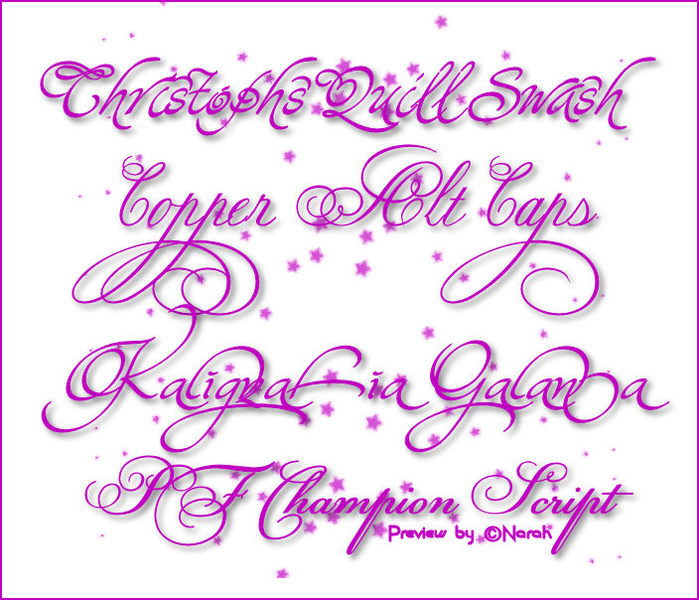
Бесплатно шрифты для фотошопа: Скачать бесплатные шрифты для Photoshop
Многие пользователи сталкиваются с такой ситуацией, когда нужен какой-то необычный и уникальный шрифт в фотошопе. К примеру, при создании поздравительной открытки, афиши и т.д. Стандартного набора шрифтов уже становится мало.
2. Установка шрифтов в Windows.
Здесь уже можно просмотреть все установленные в вашей операционной системе шрифты. Сама процедура установки происходит несколько иначе. Здесь нужно в меню «Файл» выбрать пункт «Установить шрифт».
Далее откроется окошко выбора шрифтов. Нужно открыть папку, в которой лежат файлы новых шрифтов, а затем выделить те из них, которые нужно установить. В конце жмем «Ок» и дожидаемся окончания процедуры.
Особенность данного способа – установленные шрифты будут доступны во многих программах, однако сам Photoshop может и не увидеть некоторые из этих шрифтов.
Поэтому, если новые шрифты нужны вам исключительно для фотошопа, то целесообразно пользоваться 1 методом установки.
10 лучших шрифтов Photoshop для использования в Creative Cloud
Типография – одна из самых красивых и разочаровывающих частей графического дизайна. Гарнитуры могут оказать огромное влияние при правильном использовании. И наоборот, к сожалению, тоже верно. Имея это в виду, вот лучшие шрифты Photoshop, доступные в качестве стандарта.
Выбор правильного семейства шрифтов
При поиске подходящего семейства шрифтов – и есть много доступных вариантов – как вы решаете, какой из них подходит именно вам? Photoshop CC поставляется с различными встроенными шрифтами, полезными для любого случая, и мы постарались найти лучшие для вас.
Прежде чем мы начнем, если вы новичок в типографии, мы рекомендуем вам проверить наше объяснение наиболее важных терминов типографии
5 самых важных типографских терминов
Прочитайте больше
, Это поможет вам понять, о чем мы говорим в оставшейся части статьи.
1.
Начнем с Times New Roman. Вы ищете шрифт, который легко читается или не слишком кричащий? Тогда Times New Roman – одна из ваших лучших ставок. Это один из самых широко доступных шрифтов, и Photoshop сделал все возможное, включив его в программу.
Первоначально созданный в 1920-х годах, Times New Roman обычно используется для основного текста в газетах, журналах и книгах. Это одобрено для его удобочитаемости и его универсального доступа через цифровые программы.
2. Баскервиль
Еще одним «классическим» шрифтом, который поставляется с Photoshop, является Baskerville: гладкая, немного «более легкая» альтернатива Times New Roman, с такими же легкими для чтения способностями и консервативным использованием пространства. Это не займет много места на странице, когда вы примените его.
Хотя Баскервиль не так популярен, как Times New Roman, он одинаково хорошо подходит для основного текста и может функционировать как текст для вашего заголовка.
3. Американская пишущая машинка
Вы ищете шрифт с засечками, который хорошо работает как основной текст в абзаце? Хотите что-то более современное и повседневное, чем Times New Roman? American Typewriter – хороший ответ на этот вопрос, и он может придать вашим документам «ретро» вид.
4. Edwardian Script ITC
Теперь, когда мы прошли основы, что если вам нужен шрифт, похожий на рукописный скрипт?
В Photoshop есть пара таких, но одним из лучших является ITC Edwardian Script: элегантный, хорошо сбалансированный шрифт, который отлично смотрится на свадебных приглашениях, поздравительных открытках и приглашениях на вечеринки.
Однако мы не рекомендуем использовать этот текст для основного текста, потому что он не такой разборчивый, как другие в этом списке.
5. Монтсеррат
Конечно, не все шрифты будут выглядеть «классически», как и вы.
Возможно, вы ищете удобный для Интернета шрифт, который хорошо выглядит на мобильных устройствах, или что-то, что ближе к современным тенденциям дизайна. Одним из наиболее полезных шрифтов, попадающих в эту категорию, является Монтсеррат с жирными, широкими буквами, что делает его идеальным для названий и заголовков. Я использовал это на своем собственном сайте в течение многих лет.
Слово предупреждения – этот шрифт не подходит для основного текста. Его большой размер означает, что это космический убийца.
6. В. Готика
Century Gothic – это шрифт без засечек с чистым, более легким на вид линейным весом по сравнению с чем-то вроде Montserrat. Вы можете использовать его для заголовков и заголовков, и если вы будете осторожны, это также хорошо для коротких абзацев. Но будьте осторожны, если эти абзацы слишком длинные, Century Gothic затруднит их чтение.
7. Helvetica
Трудно выбрать, какие шрифты являются лучшими, потому что их так много. Отчасти это зависит и от личного вкуса. Если вы ищете простую современную гарнитуру, которая работает практически со всеми дизайнами – от профессиональных отчетов до туристических брошюр – тогда лучше всего использовать Helvetica.
Helvetica – это широко используемый шрифт, который славится своей универсальностью и удобочитаемостью. Он хорошо работает для заголовка, заголовков и основного текста, а поскольку буквы расположены так красиво, что сложно испортить свой дизайн после их применения.
8. Фосфат
Лучше всего сохранить «Фан» на последний раз, верно? Мы знаем, ужасный каламбур, но иногда вы хотите веселый шрифт для рекламы. Одним из лучших вариантов, включенных в Photoshop, является Phosphate – смелый, широкий шрифт, идеально подходящий для привлекающих внимание заголовков на постерах. Из-за его размера мы не рекомендуем использовать его для основного текста, но он отлично подходит для заголовков.
9. Баухауз 93
Ищете декоративный шрифт, который немного более пышный, дружелюбный и причудливый, чем фосфат? Баухауз 93 сделает свое дело. Как и его более тяжелый сосед, этот шрифт большой и жирный, и его лучше всего использовать для заголовков на плакатах и брошюрах.
10. Браггадосио
Наконец, что не менее важно, одним из лучших дизайнов в Сан-Сериф в Photoshop является Braggadocio – смелый, гиперстиллизованный шрифт, который сразу же требует внимания. Это хорошо для названий с ретро-дизайном, но используйте его экономно. Слишком много, и это сделает ваш текст трудным для чтения.
Каков лучший шрифт Photoshop для вас?
Теперь, когда вы получили представление о шрифтах, которые поставляются с Photoshop, вы должны попробовать их, чтобы увидеть, какие из них соответствуют вашим личным вкусам.
Как упоминалось ранее, дизайн может быть субъективным, и могут быть некоторые шрифты, которые не попали в этот список, который, по вашему мнению, лучше подходит для ваших документов. Мы рекомендуем вам просмотреть их все и посмотреть, что работает лучше для вас.
Если вы изучаете полный типографский пакет Photoshop и все еще не удовлетворены имеющимся выбором, вы всегда можете использовать сайт с гарнитурой для поиска и загрузки бесплатных семейств шрифтов. У нас есть список сайтов, которые помогут вам найти бесплатные шрифты в зависимости от внешнего вида.
Как найти бесплатные шрифты, похожие на платные шрифты по внешнему виду
Поиск идеального шрифта может быть проблемой, особенно если вы не можете позволить себе заплатить за него. Но с помощью этих инструментов вы сможете найти бесплатные альтернативы в течение нескольких минут.
Прочитайте больше
,
Узнайте больше о: Adobe Photoshop, шрифты, типографии.
5 функций программного обеспечения Google Pixel Camera, которые вы должны использовать
Шрифты для Фотошопа русские
Начинаем серию записей, где будут представлены кириллические шрифты, которые можно использовать для написания русский букв в программе Adobe Photoshop. Скачать шрифты для Фотошопа можно бесплатно с ЯндексДиска по прямым ссылкам. Любой шрифт можно использовать в Фотошопе CS6, CS5, CS4, CS3, CS2 и любой другой версии.
Для установки шрифта для Adobe Photoshop, его следует скачать и переместить в папку со шрифтами на рабочем компьютере, где установлен сам Фотошоп. В Windows 7 это папка: C:\Windows\Fonts или Панель управления\Оформление и персонализация\Шрифты.
Русский шрифт Parnas Deco
Красивый русский шрифт для Фотошопа, который подойдёт для создания большинства печатных изданий и иллюстраций.
Скачать бесплатно русский шрифт для Фотошопа Parnas Deco: СКАЧАТЬ ШРИФТ (с ЯндексДиска)
Русский шрифт Pasadena Deco
Данный русский шрифт для Adobe Photoshop отличается начертанием и тем, что и прописные и заглавные буквы в шрифте преобразуются в один стиль с заглавными буквами.
Скачать бесплатно русский шрифт для Фотошопа Pasadena Deco: СКАЧАТЬ ШРИФТ (с ЯндексДиска)
Русский шрифт PosteRetro
Заглавные буквы в этом шрифте отличаются от прописных лишь добавлением теней. Размеры прописных и заглавных букв практически одинаковые.
Скачать бесплатно русский шрифт для Фотошопа PosteRetro: СКАЧАТЬ ШРИФТ (с ЯндексДиска)
Русский шрифт Proletariat
В этом шрифте и прописные и заглавные буквы одинаковые.
Скачать бесплатно русский шрифт для Фотошопа Proletariat: СКАЧАТЬ ШРИФТ (с ЯндексДиска)
Русский шрифт New Record
Красивый русский шрифт для Adobe Photoshop, имитирующей письмо ручкой.
Скачать бесплатно русский шрифт для Фотошопа New Record: СКАЧАТЬ ШРИФТ (с ЯндексДиска)
Русский шрифт Rondo Twin
Скачать бесплатно русский шрифт для Фотошопа Rondo Twin: СКАЧАТЬ ШРИФТ (с ЯндексДиска)
Русский шрифт SambaC
Необычный шрифт, который отличает особенное начертание отдельных букв, в основном — согласные буквы.
Скачать бесплатно русский шрифт для Фотошопа SambaC: СКАЧАТЬ ШРИФТ (с ЯндексДиска)
Русский шрифт Severina
Простой русский шрифт для Photoshop с одинаковым начертанием заглавных и прописных букв.
Скачать бесплатно русский шрифт для Фотошопа Severina: СКАЧАТЬ ШРИФТ (с ЯндексДиска)
Русский шрифт Stradivari script
Не шрифт, а музыка! Красивые буквы, особенно строчные.
Скачать бесплатно русский шрифт для Фотошопа Stradivari script: СКАЧАТЬ ШРИФТ (с ЯндексДиска)
Photoshop Text
Here, you will learn the process of creating bloody text effect in Photoshop by using layer styles. Step 2 > Add Some Text Write anything you want over the texture. If you want to modify an existing Photoshop shortcut or create custom Photoshop shortcuts for commands that have no default shortcut, follow the instructions below: In Photoshop, go to Edit > Keyboard Shortcuts, or hit Alt + Shift + Ctrl + K (a shortcut to access the shortcut!). Creating amazing 3D text effects is one of the many things that can be done with all the available 3D Tools and Settings in the (relatively) new Photoshop Cs6’s 3D environment. Our Picsart Photo editing platform giving all latest Text Png from here.
Скачать бесплатные шрифты Photoshop | 50 лучших бесплатных шрифтов Photoshop
Если вы столкнулись с задачей добавления текста к фотографии, эти бесплатные шрифты Photoshop, разработанные профессиональными ретушерами фотографий, будут вам очень полезны. Не кладите поверх изображения первый попавшийся шрифт, ищите замечательный шрифт, который гармонично впишется в ваш фотографический стиль. Для вашего удобства команда FixThePhoto выбрала лучшие бесплатные шрифты для Photoshop, подходящие для различных типов фотографии.
50 бесплатных шрифтов для Photoshop
№1 Акиметр. Шрифт с простыми, легко читаемыми буквами подойдет для любого изображения, передающего важное сообщение. Края букв дополнены засечками для изысканного вида.
# 2 Apogear. Это лучший шрифт Photoshop, который можно применить, если вы хотите, чтобы текст выделялся. Он сочетает в себе толстые и тонкие линии с круглыми завитками.
Лучшие шрифты для фотографии — Выбор CreativeMarket
Загрузите шрифты в рекламных целях или для публикации в социальных сетях.Вы можете легко нанести текст на свои фотографии или дизайн в Ps.
Выберите шрифт, который соответствует вашему стилю и ощущениям от вашего искусства.
# 3 Aquataken . Еще один чистый шрифт, с небольшими дополнительными засечками по краям букв. Это универсальный фотографический шрифт, который наверняка впишется в любое изображение.
# 4 Аркон. Это один из лучших профессиональных шрифтов, для которого характерны слегка вытянутые буквы. Благодаря своей простоте он широко используется в печатных СМИ.
№ 5 Артоника. Считается одним из лучших полностью читаемых бесплатных шрифтов Photoshop для фотографий логотипов. Сочетание тонких и толстых линий, острых и закругленных краев придает тексту изысканный вид.
# 6 Необычные шрифты. Это бесплатный генератор шрифтов, который позволяет преобразовать текст в стильный шрифт прямо в браузере. Вам просто нужно ввести текст, выбрать понравившийся шрифт и скопировать
№ 7 Бардане. Если применить этот шрифт к тексту, он обязательно бросится в глаза. Необычное сочетание тонких и толстых штрихов, изогнутых завитков и случайных линий, расположенных внутри, на или под буквами, гармонирует с любым творческим фото-фоном.
№8 Буке. Если вам нужно привлечь внимание к тексту или сделать его более заметным, этот шрифт подойдет идеально. Он имеет жирные и толстые буквы с изогнутыми штрихами, которые выглядят довольно привлекательно.
№ 9 Кардоне. Входит в список лучших шрифтов Photoshop. Этот шрифт часто используется для текста, который выражает всевозможную информацию из-за единообразной формы букв и аккуратного внешнего вида.
№ 10 Карридж. Это один из лучших рисованных бесплатных стилей шрифтов Photoshop. Его уникальные изгибы и штрихи определенно модернизируют любой текст или заголовок.
№11 Чалсын. Это отличный шрифт с засечками для тех, кто ищет шрифты для логотипов фотографий.Буквы характеризуются тонкими и простыми линиями, которые способствуют освежающему виду текста.
№ 12 Читоса. Это один из самых узнаваемых шрифтов Photoshop для кистей. Смесь замысловатых линий и завитков добавит вашему тексту изюминки.
# 13 Чусарский. Вы не ошибетесь с этим шрифтом с засечками, если вам нужно, чтобы текст выглядел достаточно просто и минималистично. Буквы средней толщины с четкими линиями впишутся в любой образ.
# 14 Констанца. Название этого шрифта говорит само за себя — буквы постоянной формы, которые выглядят слегка жирными. Этот шрифт с засечками рекомендуется использовать для заголовков, например, на веб-сайтах.
# 15 Contaria. Это один из наиболее подходящих бесплатных шрифтов для съемки природы и пейзажей. Его округлые края дарят ощущение умиротворения и умиротворения.
# 16 Даулинк. Геометрические протяженные буквы шрифта дополнены тонкими и неровными мазками.Применяйте его, если вам нужно добиться гранжевого эффекта текста.
# 17 Затмение. Если вы ищете бесплатные шрифты для дизайнеров, то это один из них. Нежные и слегка закругленные края, разнообразное вращение букв сразу привлечет внимание к картинке и тексту.
# 18 Enjoyinalos. Еще один необычный шрифт, который выглядит так, будто нарисован кистью. Из-за этого эффекта буквы содержат пробелы, но они не усложняют чтение слов.
# 19 Envatic. Это один из самых простых и разборчивых бесплатных шрифтов Photoshop. Аккуратные и точные буквы отлично будут смотреться на однотонных и монохромных изображениях.
№20 Эполос. Он считается одним из самых элегантных шрифтов для подписи Photoshop. Буквы с точками по краям, красиво изогнутые длинные линии выглядят как настоящий почерк прошлых веков.
№ 21 Фантартика. Этот шрифт может служить отличным шрифтом для подписи. Соединенные буквы с изысканными завитками украсят любую фотографию и текст на ней.
№ 22 Пожарные. Среди лучших шрифтов для логотипов этот привлекает больше всего внимания. Благодаря своим особенностям, таким как неровные и слегка вытянутые буквы, шрифт эффективно используется для брендинга или упаковки.
№ 23 Фонтанце. Если вы ищете шрифты водяных знаков для фотографий, обратите внимание на этот.Его характеристики включают в себя тонкие завитки и жирные буквы с отчетливыми пустыми линиями, пронизывающими шрифт.
№ 24 Фраголлини. Шрифт навеян надписью на классной доске. Внутренние части букв покрыты тонкими неровными линиями. Вы можете применить этот шрифт к своим логотипам или для того, чтобы подчеркнуть название бренда.
№ 25 Готемика. Шрифт — прекрасное дополнение к списку рукописных гарнитур.Изысканные буквы с дополнительными завитками идеально впишутся в любой вид фотографии.
# 26 Ханстер. Еще один отличный рисованный бесплатный шрифт для Photoshop. Буквы с тонкими штрихами и завитками подходят как для профессиональных, так и для повседневных целей.
# 27 Linteras. В шрифте сочетаются толстые и тонкие линии с плавными изгибами. Буквы соединены и идеально подходят для применения к цитатам.
# 28 Litecrossin. Это очень минималистичный и легкий для чтения шрифт с чистыми линиями. Вам может потребоваться обвести текст этим шрифтом, чтобы слова были более заметными.
# 29 Ломарин. Этот шрифт невероятно сочетает жирные буквы с слегка изогнутыми краями. Используйте его, когда вам нужно сделать сильное заявление и привлечь внимание к тексту.
# 30 Меланна . Его можно охарактеризовать как один из самых изысканных бесплатных шрифтов для фотографии.Можно нанести буквы средней толщины с небольшими изгибами, чтобы выделить заголовок или цитату.
# 31 Midvalence. Это отличный бесплатный шрифт для Adobe Photoshop, немного похожий на Linteras. Но в этом шрифте буквы не связаны друг с другом, что делает его идеальным вариантом для заголовков, длинных или коротких.
№ 32 Монпанс. Среди бесплатных шрифтов для дизайнеров этот, безусловно, самый необычный.Буквы выглядят как настоящий, слегка неразборчивый почерк. Хотя это может быть отличным шрифтом для подписи, не рекомендуется использовать его для передачи важной информации.
# 33 Монрета. Если вы ищете универсальный шрифт, вы можете попробовать этот. Это шрифт с засечками, характеризующийся простыми и четкими буквами.
№34 Наласкина. Считается одним из лучших шрифтов для фотографов.Тонкие изящные буквы красиво сочетаются с любым фоновым изображением.
# 35 Оракл Дарк. Название шрифта может указывать на то, что он предназначен для мрачных и драматических снимков. На самом деле он вполне приемлем для различных целей из-за средней толщины букв с тонкими изогнутыми линиями.
# 36 Паладин. Этот шрифт входит в список лучших бесплатных шрифтов для скачивания. Преимущество заключается в его универсальности, аккуратности и точности надписей, подходящих для названий или упаковки.
№ 37 Патаганиар. Это один из самых фантастических бесплатных шрифтов для логотипов Photoshop. Его особенностями являются тонкие и изогнутые двустрочные буквы, которые также дополнят подходящий фото-фон.
№38 Президиум. Этот шрифт увеличивает список превосходных рисованных бесплатных шрифтов Photoshop. Курсивные буквы детализированы дополнительными завитками.
№ 39 Пурбанк. Охарактеризован как один из самых изысканных шрифтов фотографии. Сплошные, рукописные и слегка изогнутые буквы могут улучшить внешний вид любого текста.
№40 Растан. Он считается одним из многих привлекательных шрифтов Adobe Photoshop, которые можно бесплатно загрузить. Шрифт имеет нарисованные от руки буквы с небольшими изгибами, которые улучшат, например, изображение с коротким заголовком или цитатой.
# 41 Скристофер. Как один из самых ярких бесплатных шрифтов для подписи, его характеристики включают тонкие линии букв и изогнутые штрихи.Благодаря узнаваемому стилю, его также можно использовать для логотипов или заголовков.
№ 42 Шрамель. Вам никогда не хватит минималистичных бесплатных шрифтов Photoshop с засечками. Простые и чистые буквы этого шрифта средней толщины подходят для текста на однотонном фоне.
# 43 Сонтара. Этот шрифт по праву занимает свое место среди лучших шрифтов для фотошопа. Слегка закругленные буквы с изогнутыми краями определенно модернизируют внешний вид текста.
# 44 SpiritCon. Считается одним из лучших бесплатных шрифтов для дизайнеров. Очень тонкие буквы с небольшими изящными завитками обязательно увеличат «дух» вашего текста и изображения в целом.
# 45 Sunnysan. Еще один отличный шрифт среди упрощенных шрифтов для загрузки в Photoshop. Он имеет слегка вытянутые буквы одинаковой формы для четкого вида текста.
# 46 Валенс. Этот шрифт дополняет список невероятных бесплатных шрифтов Photoshop. В глаза бросается смесь толстых и тонких мазков с закругленными краями.
# 47 Винбарри. Шрифт имеет схожие характеристики с Valense. Только буквы у этого не наклонены, и его можно использовать в более профессиональных целях, например, для обложки журнала или книги.
№ 48 Виолетта. Он считается одним из лучших бесплатных шрифтов для Photoshop.Его изящные изогнутые буквы напоминают ретро-почерк. Из-за его особенностей используйте этот шрифт, чтобы добиться драматического эффекта.
№ 49 Виртуозо. Судя по названию, это один из самых необычных шрифтов с водяными знаками для фотографии. Вытянутые тонкие линии, большая разница между заглавными и строчными буквами оставят неизгладимое впечатление.
№ 50 Юнграндер. Это один из тех бесплатных шрифтов для Adobe Photoshop, которые на первый взгляд могут показаться обычными. Но на самом деле в его простоте и небольших завитках есть определенное очарование, которое может броситься в глаза при правильном применении шрифта.
Попробуйте и загрузите шрифты для Photoshop, разработанные FixThePhoto. Возможно, вам придется пройти через приличное количество из них, чтобы найти самые замечательные и вдохновляющие шрифты, но не бойтесь экспериментировать.
33 лучших бесплатных шрифта, которые следует загрузить дизайнерам
Поиск стильных шрифтов для ваших дизайнерских проектов может отнять у вас много времени, особенно когда вам приходится пробираться через кажущиеся бесконечными страницы шрифтов, которые не подходят для вашего видения. .
Найти бесплатный шрифт может быть еще сложнее.
Так что же делать дизайнеру с ограниченным бюджетом?
Мы исследовали все глубины Интернета, чтобы вам не приходилось делать это, придумав 33 лучших бесплатных шрифта, которые вы заслуживаете иметь на своем компьютере. Вот как мы их отсортировали:
Многие из представленных здесь бесплатных шрифтов были разработаны дизайнерами для дизайнеров, поэтому они не понаслышке понимают необходимость универсальных, отполированных и бесплатных шрифтов. Ознакомьтесь со шрифтами ниже и помните о них в своем следующем дизайнерском проекте.
Лучшие бесплатные шрифты для дизайнеров
- Hello Stockholm — шрифт скрипта
- Wildera Regular — шрифт шрифта
- Mightype — шрифт скрипта
- Selima — шрифт скрипт
- Oranienbaum Regular — шрифт с засечками
- Butler — шрифт с засечками
- Arctic — шрифт с засечками
- Canvas — шрифт с засечками
- Bitter ht — шрифт с засечками
- Agne Regular — шрифт с засечками
- Yeseva One Regular — шрифт с засечками
- Moon — современный шрифт
- Kolikö — современный шрифт
- Mohave — современный шрифт
- 20 дБ
- Alcubierre Regular — современный шрифт
- Bourbon Grotesque — современный шрифт
- Frontage Outline — современный шрифт
- Arciform Sans Regular — современный шрифт
- De La Fuente — современный шрифт
- Westfalia — шрифт для логотипов
- Atami — шрифт для логотипов
- Anders — шрифт для логотипов
- Westmeath — шрифт для логотипов
- Modeno — шрифт для логотипов
- Rezland — шрифт для логотипов
- Polya — шрифт для логотипов
- Horizon — ретро шрифт
- Sweet Sensations — ретро шрифт
- ITC Bauhaus — ретро шрифт
- Bobbers — ретро шрифт
- FF Blur — ретро шрифт
- Canterbury — ретро шрифт
Бесплатные скриптовые шрифты
1.
Что произойдет, если совместить скандинавский минимализм с классическими мазками? Вы получаете Hello Stockholm , случайный сценарий, который хорошо сочетается со шрифтами без засечек.
2. Wildera Regular
Мы думаем, что этот причудливый, легкий сценарий будет хорошо смотреться в сказке (или в вашем следующем проекте).
3. Mightype
Тонкие детали, нарисованные от руки, отличают этот сценарий от набора. Mightype изысканный, но не душный.
4. Селима
свежих мазков Селимы — прекрасное доказательство того, что шрифтовые шрифты не обязательно должны выглядеть старомодно или напряженно — они могут быть повседневными и современными.
Бесплатные шрифты с засечками
5. Ораниенбаум Обычный
Многозадачность — от мелкого шрифта до жирных заголовков — Oranienbaum справится с задачей.
6. Дворецкий
Совершенно современный шрифт с засечками, Butler , выпускается в 14 вариантах начертания, чтобы удовлетворить самые разные задачи.
7. Арктика
Если вы ищете шрифт с плоскими засечками с современными краями, попробуйте Arctic . Это отличный способ придать заголовкам особый характер.
8. Холст
Canvas предлагает скромный, но профессиональный шрифт, который изменяет толщину деталей каждой буквы. Если вы ищете формальности и креативности в одном и том же шрифте, этот вариант лучше всего.
9. Горький ht
Нам нравится универсальность Bitter ht, — современного шрифта с засечками, который выглядит стильно при любом размере и весе.
10. Agne Regular
Этот элегантный шрифт с жирными линиями и контрастными основами представляет собой свежий взгляд на старомодные гарнитуры с засечками.
11. Есева Один Обычный
Если вас беспокоит, что шрифты с засечками кажутся слишком строгими или формальными, рассмотрите вариант Yeseva , непринужденный вариант для заголовков и субтитров.
Бесплатные современные шрифты
12. Луна
Вы исчерпали свою библиотеку простых и бесплатных шрифтов без засечек? Добавьте к смеси Moon .Нам нравится чистая простота и округлые края этого шрифта.
13. Kolikö
Этот жирный шрифт придает загадочность любой творческой работе. Или, если вы просто хотите узнать о чем-то в своем новом техническом блоге, мы можем полностью увидеть, что этот шрифт играет определенную роль.
14. Мохаве
Этот шрифт, состоящий только из заглавных букв, был разработан с учетом жирных заголовков и больших настроек шрифта.
15. 20 дБ
Шрифт ниже просто неподвластен времени. Независимо от того, разрабатываете ли вы рекламу мероприятия или заголовки своего блога, 20 дБ — это уверенность в письменной форме.
16. Alcubierre Regular
Чистый, минималистичный и геометрический, Alcubierre хорошо подходит для проектов, требующих тонких заголовков и четкого акцента на содержании.
17. Бурбонский гротеск
Вдохновленный, как вы уже догадались, классическими этикетками из бурбона, этот без засечек обладает яркой индивидуальностью, требующей внимания.
18. Внешний вид
Frontage Outline напоминает фасадные вывески ручной работы, что делает его подходящим выбором для логотипов.
19. Arciform Sans Regular
Arciform может быть простым, но этот гладкий шрифт без засечек далеко не скучный. Подумайте о том, чтобы включить этот легкий для чтения шрифт в свой следующий проект веб-дизайна.
20. Де Ла Фуэнте
Этот классный шрифт является декоративным, но не чрезмерным, что делает его идеальным для заголовков, логотипов и других дизайнерских проектов, в которых основное внимание уделяется тексту.
Хорошие шрифты для логотипов
21. Вестфалия
Придайте своему следующему проекту атмосферу естественности и аутентичности с помощью этой расписанной вручную кисти без рисунка, которая также создает игривый логотип.
22. Атами
Многочисленные веса и варианты отображения Atami делают его швейцарским армейским ножом среди современных шрифтов без засечек — он действительно может сделать все это для растущего бренда.
23. Андерс
Anders может стать авангардным шрифтом вашей мечты. Уникальные геометрические линии делают его отличным выбором для логотипов.
24. ВестмитWestmeath добавляет немного чванства к основному шрифту, делая логотип, использующий этот шрифт, разборчивым и стильным.
25. Модено
Шрифт Modeno соответствует тонкому дизайну, к которому в последние несколько лет тяготели многие современные художники. Но не путайте этот шрифт с любым шрифтом новой волны — его долговечные качества трудно найти в сегодняшних вариантах без засечек.
26. Резланд
Резланд просто крут. У него почти нет времени для вас … вот насколько круто этот выбор шрифта.
27.Поля
Polya , пожалуй, самый интересный шрифт, который мы могли найти. Тесьма каждой буквы создает поистине завораживающий логотип.
Бесплатные ретро шрифты
28. Горизонт
Horizon — простой, но ретро-шрифт, воспроизводящий изображения старого космического фильма. И тем не менее, он все еще остается в силе.
29. Сладкие ощущения
30. ITC Bauhaus
Подобно Horizon, ITC Bauhaus имеет округлый ретро-вид, который бывает разной толщины.Более толстые версии выглядят как заголовок старой афиши, а более тонкие стили создают джазовую атмосферу.
31. Бобберы
Bobbers — это скриптовый шрифт, обладающий бестолковыми и чрезмерными качествами старого комедийного сериала. Верните его из 1970-х в свой следующий дизайн-проект для действительно уверенного заголовка.
32. Размытие FF
Призрачное сияние FF Blur напоминает нам старый фильм ужасов. Но он может быть достаточно мягким, чтобы заинтриговать аудиторию вашего следующего проекта.
33. Кентербери
Ни один список старомодных шрифтов не будет полным без староанглийского стиля Кентербери. Подражайте многим из самых известных сегодня газетных логотипов с помощью этого традиционного шрифта.
Мы надеемся, что вы найдете эти шрифты полезными, но поскольку они предлагаются другими сторонами на их сайтах, мы не можем давать никаких гарантий или обещаний в отношении них (например, что они будут доступны или бесплатны для использования).
Также мы хотим упомянуть, что дизайнеры, предлагающие эти шрифты, могут иметь правила о том, как вы можете или не можете их использовать, поэтому могут быть ограничения, применимые к использованию шрифта.
Хотите больше советов по шрифтам? Ознакомьтесь с этим советом по определению названия шрифта.
25 великолепных бесплатных шрифтов для вашего следующего дизайн-проекта
Шрифты для дизайнеров — то же самое, что обувь для женщин. Их никогда не может быть достаточно. А что лучше красивого шрифта? Красивый шрифт, доступный БЕСПЛАТНО. Мы составили список из 25 стильных и современных шрифтов, которые понравятся дизайнерам.Ознакомьтесь с ними ниже.
1. Луна
Скачать шрифт2. Бухты
Скачать шрифт3. Большой Джон / Тонкий Джо
Скачать шрифт4. Барон
Скачать шрифт5. Порту
Скачать шрифт6. Элероны
Скачать шрифт7. Винтаж и эрозия
Скачать шрифт8. Акцентный дисплей
Скачать шрифт9. Simplifica
Скачать шрифт10.Андерс
Скачать шрифт11. Бесконечность
Скачать шрифт12. Мохаве
Скачать шрифт13. Adam.CG Pro
Скачать шрифт14. Aqua Grotesque
Скачать шрифт15. Байдарка Sans
Скачать шрифт16. Причал
Скачать шрифт17. Котенок
Скачать шрифт18. Бесом
Скачать шрифт19.Moderne Sans
Скачать шрифт20. Мантека
Скачать шрифт21. Фасад
Скачать шрифт22. Ось
Скачать шрифт23. Коко
Скачать шрифт24. Плотный
Скачать шрифт25. Код
Скачать шрифтПОДРОБНЕЕ…
Какой ваш любимый? Надеюсь, этот пост пригодился. Поделитесь этим постом с другом-дизайнером и выскажите свое мнение в комментариях ниже.
Не пропустите:
- 32 блестящих логотипа со скрытым смыслом
- Графический дизайнер исправил 9 худших логотипов в истории
- 10 лучших документальных фильмов Netflix для графических дизайнеров
- Google AutoDraw бесплатно превращает ваши грубые каракули в красивые значки
- 30 Отличные сочетания шрифтов для вашего следующего дизайн-проекта
- 15 отличных сочетаний шрифтов Google для вашего следующего дизайн-проекта
профессиональных шрифтов | FontSpace
Загрузить- Темный режим
- Помощь Войти
- Шрифты
- Стили
- Коллекции
- Генератор шрифтов
- (͡ ° ͜ʖ ͡ °)
- Дизайнеры бесплатно
Cool
Cursive
Script
Симпатичный
Рукописный ввод
9035 903 903 903
9035 Serial
Современный
Логотип
Декоративный
Элегантный
Закругленный
Красивый
9028
- 9035 9035 Чистый
- 9035
Ссылка
Unicode
Название
Заголовок
Футуристический
Capital
Классический
SpaceДисплей
Заголовок
Брендинг
Женский
Журнал
Техно
28 Корпоративный- используйте
Сортировать по
- Популярные
- В тренде
- Новейший
- Имя
Личное использование Бесплатно
856k загрузок
Персональное использование Бесплатно
Обычный8420 загрузок
Для личного пользования Бесплатно
9993 загрузки
Личное использование Бесплатно
160.7k загрузок
Personal Use Free
26476 загрузок
Личное использование Бесплатно
152.9k загрузок
100% бесплатно
Обычные21694 загрузки
Для личного пользования Бесплатно
6588 загрузок
Личное использование Бесплатно
Straight Regular8286 загрузок
Personal Use Free
89665 загрузок
Личное использование Бесплатно
323 загрузки
100% бесплатно
Обычный9571 загрузок
Для личного пользования Бесплатно
287.1k загрузок
Personal Use Free
54116 загрузок
Личное использование Бесплатно
51627 загрузок
От 1 до 15 из 306 Результаты
- 1
- 2
- 3
- 4
- Next
Еще больше стилей
0
- Популярные шрифты
- Коммерческие шрифты
- Классные шрифты
- Курсивные шрифты
- Блог
- Справка
- Связаться с
- Бренд
- Конфиденциальность
- Условия
- DMCA 921-2010
60 великолепных и креативных бесплатных шрифтов для дизайнеров
2Добро пожаловать на третий день недели бесплатного пользования на Designrfix.Сегодня мы собрали потрясающую коллекцию самых красивых и креативных бесплатных шрифтов для дизайнеров. Так что, если вы ищете действительно классные бесплатные шрифты для своего последнего проекта, этот пост нельзя пропустить. Не стесняйтесь загружать и использовать их в своем следующем дизайне. Надеюсь, они вам понравятся, и завтра смотрите следующую бесплатную партию!
Хотите больше статей из Freebie Week ? Ознакомьтесь с некоторыми из наших предыдущих сообщений:
Бесплатные файлы PSD: более 50 файлов Photoshop, которые необходимо иметь для дизайнеров
40 бесплатных иконок социальных сетей с хорошим дизайном
Связано: Получите логотип за считанные минуты с помощью бесплатного конструктора логотипов от designhill.com
[m2leep]Лента
[AdSense]Intro бесплатный шрифт
Шрифт Stiff Staff
Архив
ГУБЕРНАТОР АЛФАВИТА АРТ ДЕКО
РБNo2
килограмм
бесконечность
Шрифт Hagin
Prime Шрифт
FV Алмело
[AdSense]Rex Бесплатный шрифт
Forum Шрифт
КОД Pro
Color Lines Бесплатный шрифт
Шрифт KanKin
Habana Шрифт
Cube 02 шрифт
Cube шрифт
Бендер Шрифт
Muncie Шрифт
CROISSANT — Бесплатный веб-шрифт Google
NULL Бесплатный шрифт
Cassannet Шрифт
[AdSense]Facunda Шрифт
Разноцветные шрифты
PLSTK Шрифт
Шрифт Chrome Light
Myra шрифт
Metropolis бесплатный шрифт
Баркентина Гарнитура
Шрифт Авраама Линкольна
Signika шрифт
Сценарий мудрости
Шрифт Ranger
Шрифт Blanch
Manteka Шрифт
RIDGE Гарнитура
Nelma Шрифт
Maven Pro
Шрифт Musket
Гарнитура Magna
Шрифт Origram
Code Free Шрифт
Шрифт Tetra
Шрифт Razor
Franchise Шрифт
Mensch шрифт
Валенсия Шрифт
Deming Шрифт
Duke Шрифт
Сценарий миссии
Лавандерия
Johanna Font
Цифры Pompadour
Sreda бесплатный шрифт
Atreyu Шрифт
Arvil Шрифт
Шрифт сбоя
Тип настроения
27 Красивые высококачественные бесплатные шрифты — Smashing Magazine
Время от времени мы смотрим вокруг, выбираем свежих бесплатных высококачественных шрифтов и представляем их вам в кратком обзоре.Выбор огромен, поэтому время, которое вам нужно найти, обычно — это время, когда вы должны инвестировать в свои проекты. Мы ищем их и находим, чтобы вам не пришлось. В этой подборке мы рады представить шрифты Tondu, Banda, Morning Glory, Matilde, Bohema, Weston Round Slab, Highlands, Cabin, Linden Hill и другие. Обратите внимание, что хотя большинство шрифтов доступны для коммерческих проектов, некоторые предназначены только для личного использования и четко обозначены как таковые в их описаниях. Также внимательно прочтите лицензионные соглашения перед использованием шрифтов; они могут время от времени меняться.Время от времени мы смотрим вокруг, выбираем свежих бесплатных высококачественных шрифтов и представляем их вам в кратком обзоре. Выбор огромен, поэтому время, которое вам нужно найти, обычно — это время, когда вы должны инвестировать в свои проекты. Мы ищем их и находим, чтобы вам не пришлось.
В этой подборке мы рады представить шрифты Tondu, Banda, Morning Glory, Matilde, Bohema, Weston Round Slab, Highlands, Cabin, Linden Hill и другие шрифты. Обратите внимание, что хотя большинство шрифтов доступны для коммерческих проектов, некоторые предназначены только для личного использования и четко обозначены как таковые в их описаниях.Также внимательно прочтите лицензионные соглашения перед использованием шрифтов; они могут время от времени меняться.
Дополнительная литература по SmashingMag:
Новые высококачественные бесплатные шрифты
Bohema Bohema — уникальный шрифт в стиле ар-деко в современной интерпретации. Непредсказуемость некоторых глифов делает его оригинальным и интересным, хотя иногда и немного хлопотным. Bohema доступна в восьми различных стилях и может отлично подходить для заголовков, редакционных надписей, брендинга, мерчендайзинга и особых случаев.Вы можете бесплатно загрузить один вес, Bohema Regular Alternative, хотя он не так полезен, как остальные шрифты из семейства шрифтов.
Highlands — это очаровательный шрифт с плоскими засечками, вдохновленный плакатами старых добрых национальных парков США. Шрифты, разработанные Тайлером Галпином, отлично подходят для заголовков и плакатов. В настоящее время доступен только набор заглавных букв. Выпущено по лицензии «плати сколько хочешь».
Бендер Семейство шрифтов Bender — это экстравагантный русский шрифт для особых случаев.Используйте его для графического дизайна, портфолио или полиграфической продукции. Доступны восемь размеров шрифтов, все они доступны для бесплатной загрузки. Но регистрация на MySpace обязательна.
Овальный тип Экспериментальный игривый шрифт, основанный на формах овала и круга. Очевидно, что он не подходит для корпоративных или элегантных проектов, но Ovalian Type может быть весьма полезен в проектах, которые требуют экспериментов, взаимодействия и творчества. Доступен в формате TrueType.
Linden Hill — это цифровая версия Deepdene Фредерика Гуди.Это небольшое семейство с засечками, разработанное Барри Шварцем, включает в себя римский шрифт и курсив. Linden Hill доступен в формате OpenType по лицензии SIL Open Font License.
Fanwood — это тщательно продуманный шрифт с засечками, напоминающий классический римский шрифт. Пакет шрифтов включает в себя римский и курсивный стили, оптимизированные для экрана. Это отличный шрифт, приятный при чтении, в том числе в заголовках и основном тексте. Выпущено под лицензией SIL Open Font License).
Матильда Приятный тонкий шрифт с очень высокими заглавными буквами и тонкими декоративными элементами. Матильда отлично подойдет для заголовков, коротких абзацев, детских книг, плакатов и брошюр. Семейство содержит 212 символов и глифов. Доступны два стиля: Обычный и Эскиз. Шрифт также содержит декоративные рамки и узоры.
Weston Round Slab Этот шрифт содержит закругленные плоские шрифты с засечками, разработанные Павловым специально для использования в логотипах и заголовках.Обычные и облегченные версии с заглавными буквами доступны в форматах OpenType для бесплатного скачивания.
Шрифт Banda Banda — это шрифт с полутонами с засечками, характеризующийся высокой высотой x и закругленными полутонами. Хотя изначально Banda был разработан как дисплейный шрифт, он быстро превратился в более сложный набор, состоящий из семи начертаний плюс их уважительный курсив. Банда может использоваться как для коротких отрывков текста, так и для модных демонстраций. Объединяя элегантную утонченность более тонких гирь с почти детской игристостью более тяжелых гирь, Banda — отличный универсальный исполнитель, подходящий для логотипов, заголовков, упаковки, пищевых продуктов и многого другого.
Black & White(Ссылка была удалена из-за нарушения авторских прав. Оригинальный дизайн — Calypso, разработанный литейным заводом Typolar.) Экспериментальный шрифт с двумя начертаниями шрифта (обычным и курсивом). Шрифт имеет множество отличительных игривых элементов, которые придают заголовкам неповторимый стиль ретро. Шрифт содержит английские и кириллические буквы и доступен в форматах OpenType и True Type.Обратите внимание, что в обоих форматах маленькая буква «j» не работает должным образом.Мы связались с дизайнером по поводу проблемы и надеемся, что шрифт скоро будет обновлен.(Проблема устранена.)Fabrica Practice Foundry — это независимый производитель шрифтов, выпускающий шрифты по лицензии «плати сколько хочешь». Шрифт без засечек был задуман как самый разборчивый шрифт для мобильных экранов. Его детали взяты из более систематически построенных нео-гротесков, что придает ему нейтральный тон голоса. Хотя Fabrica была разработана в первую очередь для мобильных экранов, шрифт подходит для любого приложения, большого или маленького.Шрифт доступен в формате OpenType для Mac и ПК.
ARS Новинка Этот шрифт — результат нестандартного подхода Ангуса Р. Шамала. Дизайнер придумал забавный и ни в коем случае не менее функциональный эксперимент с гибридными стилями и историческими влияниями, соединив барокко с засечками с геометрическим шрифтом без шрифта, формальный с декоративным штрихом. ARS Novelty — это, по-видимому, шрифт, который пытается все понять. Доступен единый вес со стилистическими альтернативами, цифрами, стандартными лигатурами и произвольными лигатурами, формами с учетом регистра, порядковыми и локализованными формами.В формате OpenType.
Беван Bevan — это переработка традиционного шрифта с засечками, созданного Генрихом Йостом в 1930-х годах. В Беване ранние формы букв Йоста были оцифрованы, а затем переделаны для использования в качестве веб-шрифта. Счетчики были немного приоткрыты, а штрихи оптимизированы для использования в качестве жирного шрифта в современных веб-браузерах. Это хороший выбор для жирных заголовков и рекламных брошюр. Выпущено по лицензии SIL Open Font License и доступно в репозитории Google Web Fonts.Дизайн Вернон Адамс. Возможно, вы захотите взглянуть на другие бесплатные шрифты Вернона Адамса: Rokkitt, Shanti, Muli.
Sansus Webissimo Этот шрифт представляет собой современный открытый гротескный шрифт, доступный в форматах OpenType и TrueType. Sansus потенциально отлично подходит как для заголовков, так и для основного текста, как в Интернете, так и в печати. Доступны две толщины шрифта: обычный и курсив. Семейство выпущено под лицензией Creative Commons Attribution 3.0 License.
Quattrocento Roman — классический, элегантный и сильный шрифт, которому, возможно, не хватает зрелости в некоторых деталях (например, «g» и «e» не совсем подходят друг другу).Шрифт имеет широкие и открытые буквы, а хорошая высота по оси x делает основной текст разборчивым даже при небольших размерах. Как классический римский шрифт Quattrocento — хороший выбор для крупных жирных заголовков. Исходные файлы Fontlab включены в пакет загрузки. Quattrocento Sans, доступный в виде веб-шрифта, также можно загрузить бесплатно.
Танцевальный сценарий Dancing Script — это живой и непринужденный сценарий, в котором буквы подпрыгивают и слегка изменяются в размере. Шрифт отсылает к популярным гарнитурам 50-х годов.Он напоминает Мюррея Хилла (Эмиля Клумппа, 1956) по распределению веса и Мистраля (Роджера Экскоффона, 1953) по его эффекту подпрыгивания. Dancing Script может быть полезен, если вы ищете непринужденный, дружелюбный, неформальный и спонтанный шрифт, а также неплохую замену Comic Sans! Также доступен в виде веб-шрифта.
Кабина Cabin — это гуманистический шрифт без засечек, вдохновленный шрифтами Эдварда Джонстона и Эрика Гилла с элементами модернизма. Кабина вобрала в себя современные пропорции, оптические корректировки и некоторые элементы геометрической формы.По словам дизайнера, «он остается верным своим корням, но имеет свою индивидуальность». Отличный шрифт для основного текста и заголовков на маленьких и больших экранах. Доступны четыре толщины шрифта с соответствующими стилями курсива.
Logisoso — это постоянный проект шрифтового дизайна. Шрифт, созданный во время проекта вывески для логистического центра, где он использовался для обозначения различных зданий, был позже дополнен с помощью Inkscape и сгенерирован с помощью FontForge. Пакет загрузки содержит исходные файлы для улучшения и оптимизации шрифта.
Novecento — это семейство шрифтов только с прописными буквами, вдохновленное европейскими типографскими тенденциями первой половины 20 века. Гарнитура выглядит рациональной, геометрической и блочной. Но он основан на оптических, а не геометрических пропорциях. Novecento можно использовать для заголовков, визуальных обозначений и коротких предложений. Более легкие веса придают более современный вид, а более смелые — в стиле ретро.
Ubuntu Семейство шрифтов Ubuntu — это набор новых открытых шрифтов без засечек.Семейство включает в себя все языки, используемые пользователями Ubuntu по всему миру. Разработан Далтоном Маагом для операционной системы Ubuntu и с открытым исходным кодом.
Ультра Красота Ultra заключается в ее смелости. Этот декоративный западный шрифт с элегантными засечками имеет резкое и привлекательное присутствие, особенно в тонких тонах «J», «7» и «f». Шрифт имеет расширенный европейский набор символов и доступен для бесплатной загрузки в формате TrueType. Под лицензией Apache License версии 2.
CS Бенвуд Этот шрифт уникален и подходит для самых разных работ по полиграфическому дизайну, будь то плакаты, обложки компакт-дисков или любой другой проект, требующий нетрадиционного типографского оформления. Каждый глиф имеет свой уникальный «древесный» вид. Разработано BenChalit Sagiamsak и доступно в формате OpenType.
Пять минут Этот шрифт был создан Олегом Журавлевым и предназначен для иллюстраций, отображающих ваш мозговой штурм и другие творческие идеи. Буквы не совсем оптимизированы и кажутся немного рыхлыми, но и от своих набросков большего вы не ожидаете.Шрифт содержит 151 глиф, включая латинский и кириллический алфавиты, цифры и некоторые специальные символы.
Maven Pro — это бесплатный шрифт без засечек с уникальной кривизной и плавным ритмом. Обширная коллекция символов насчитывает более 530 символов! Поддерживаются многие языки (их слишком много, чтобы перечислить), включая базовую латиницу и западноевропейские диакритические знаки. Огромное количество глифов позволяет использовать его практически для любого текстового контента: электронных таблиц, документов и особенно веб-сайтов.Шрифт также отлично подходит для печатных материалов и может очень сильно уменьшаться, сохраняя при этом разборчивость. Доступен в четырех стилях: черный, жирный, обычный и средний.
TypoFlat Основатель Typoflat Бранислав С. Циркович любит экспериментировать с шрифтом. На веб-сайте компании есть ряд экспериментальных векторных шрифтов (доступен только формат EPS), все они доступны для бесплатного скачивания и использования.
Никайя Компания Miller Type Foundry выпустила для бесплатного скачивания три толщины шрифта из своего семейства шрифтов Nikaia.Nikaia — футуристический геометрический шрифт для заголовков и основного текста. Nikaia, Nikaia Regular Italic и Nikaia Script выпущены бесплатно. Чтобы скачать файлы, вам необходимо зарегистрироваться на MyFonts.
Eau Sans Этот шрифт без засечек был первоначально разработан Ямаока Ясухиро в 1992 году, но глифы красивой формы делают его вневременным и надежным инструментом для любой типографской работы. Семейство состоит из шести начертаний шрифта с числовыми символами в трех вариантах: пропорциональный, в старом стиле и цифры с выравниванием.
Подкова представляет собой монолинейную плитку с засечками с диагональными окончаниями. Широкие пропорции и чистые элементы помогают разборчивости на небольших размерах. Необычные формы букв обеспечивают достаточно символов, чтобы их можно было использовать на дисплеях любого размера. Создан Ильей Юдиным в 2010 году.
Last Click
Сила типографики Да пребудет с вами сила типографики! Маттео Чиваски и Джанмарко Милези доказали, что сила типографики может выходить далеко за рамки традиционного текста и заголовков. Вы когда-нибудь пробовали создать шрифтом Йоду, штурмовиков или Дарта Вейдера? Что ж, у них есть.И результат не менее впечатляющий!
Связанные сообщения
Вам могут быть интересны следующие связанные сообщения:
(al)Free For All: 103 Free Fonts!
В этом выпуске «Бесплатно для всех» я расскажу только об одном типе халявы: всеобщие любимые бесплатные шрифты! Вы найдете скриптовые шрифты, современные шрифты, забавные шрифты и многое другое. В общем, в этой статье более 100 бесплатных шрифтов — этого достаточно, чтобы даже самый крупный компьютерный фанат головокружительно строил спецификации шрифтов в течение нескольких недель!
Обратите внимание, что лицензии на шрифты ниже варьируются от личного использования до бесплатных для коммерческого использования.Некоторые из обоих типов требуют указания автора. Пожалуйста, проверьте лицензию на любой шрифт, который вы загружаете, прежде чем использовать его в проекте. И еще одно предостережение относительно бесплатных шрифтов: www.creativepro.com/blog/typetalk-are-free-fonts-worth-price.
Просто щелкните изображение, чтобы загрузить шрифт или перейти на страницу со ссылкой для загрузки. Но прежде чем вы начнете играть со своим новым типом, пожалуйста, нажмите кнопку «Комментарии» и расскажите мне, что вы хотели бы видеть в будущих выпусках «Бесплатно для всех.«Я вернусь к обычному формату пяти различных типов бесплатных ресурсов и инструментов в моей следующей статье.
Гранж шрифтыВ народе называемые «гранжевыми шрифтами», группа шрифтов, официально классифицируемых как «проблемные», впервые стала популярной в результате обращения с заголовком в телешоу 1990-х годов «Секретные материалы» (загрузите его ниже!) И тяги к их только увеличилось с тех пор. Следующие бесплатные шрифты в стиле гранж должны утолить вашу жажду — по крайней мере, на время.
Рукописные и рисованные шрифты
Подберитесь ближе и лично со шрифтами, основанными на реальном почерке других людей и на нарисованных от руки формах букв.
Больше после прыжка! Продолжайте читать ниже ↓
Пользователи Free и Premium видят меньше рекламы! Зарегистрируйтесь и войдите в систему сегодня.
Хотя «фанковые шрифты» не являются традиционной классификацией шрифтов, это лучшее описание для следующего разнообразного ассортимента шрифтов.
Эта категория зарезервирована для шрифтов, которые извлекают выгоду из большого внимания дизайнеров шрифтов к деталям и дополнительных функций, которых нет в обычном бесплатном шрифте. Некоторые из них, например, содержат данные кернинга и хинтинга почти на одном уровне с коммерческими шрифтами, за которые вы ожидаете заплатить сотню долларов или больше.Многие из них представляют собой полные гарнитуры, которые раздаются бесплатно, чтобы побудить вас приобрести дополнительные гарнитуры в более крупном семействе шрифтов. Если вам нравятся бесплатные образцы, мы рекомендуем вам заплатить за остальных членов семьи и поддержать качественный дизайн шрифта.